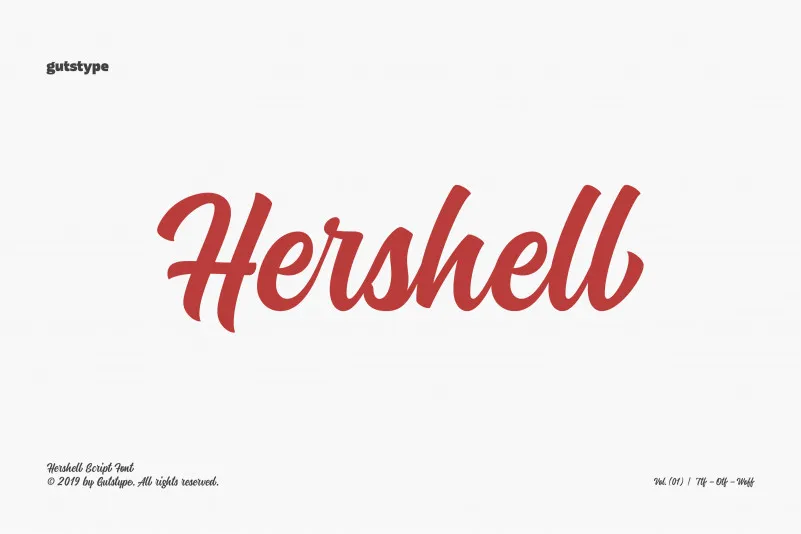
A Hershell Script é uma fonte perfeita para quem busca uma escrita elegante e envolvente, ideal para criações de branding, revistas, panfletos, etiquetas e até mesmo sinais. Desenvolvida pela Gutstype, esta fonte oferece um estilo que transmite seriedade e sofisticação sem perder a personalidade única necessária para estilos criativos. Seja em uma campanha publicitária, no design de revistas ou na criação de elementos visuais de alto nível, a Hershell Script permite que você personalize suas mensagens de maneira única e impactante. Com seu acabamento cuidadosamente elaborado, esta fonte mantém a tradição do estilo handwritten, enquanto oferece versatilidade para diferentes tamanhos e formatos. É uma escolha perfeita não apenas por sua aparência sedutora, mas também pela sua funcionalidade, fazendo dela uma opção viável para uso em qualquer aplicação gráfica que você possa imaginar. A Hershell Script é mais do que simplesmente um recurso visual; ela é um elemento essencial que pode moldar o impacto de sua marca ou projeto.